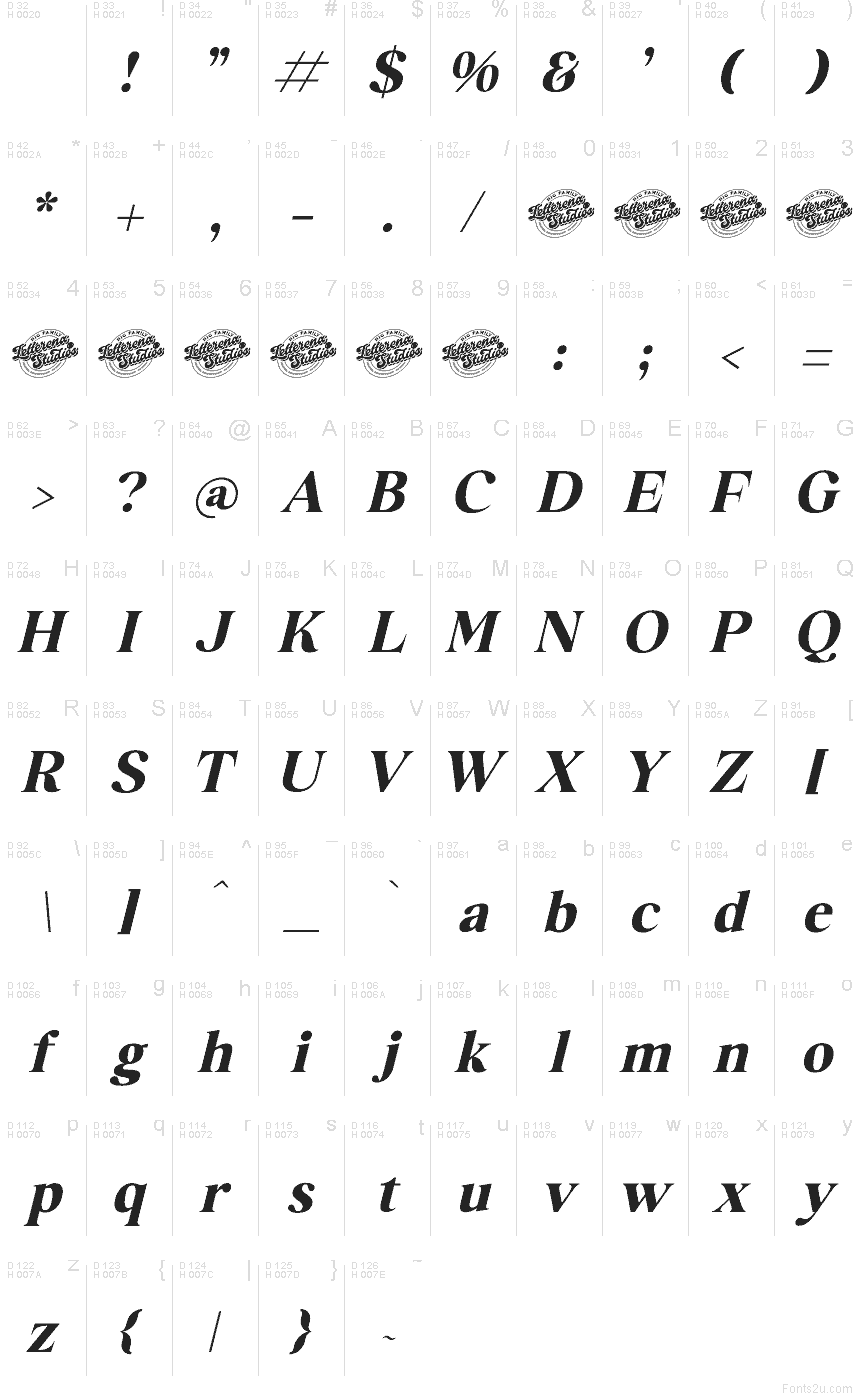
Brilyan Rogale von Letterena Studios ist eine kostenlose serifenbetonte Kursivschrift mit einer modischen, kontrastreichen Ausstrahlung. Die Buchstaben zeichnen sich durch einen eleganten, kalligrafischen Schwung aus und verbinden scharfe Serifen mit weichen Kurven – raffiniert und doch ausdrucksstark.
Sie eignet sich hervorragend für Branding-Projekte, Boutique-Verpackungen, Magazin-Cover, Hochzeitspapeterie sowie Logos aus dem Beauty- oder Schmuckbereich, bei denen eine kostenlose Schrift Eleganz ausstrahlen soll, ohne steif zu wirken. Der fließende kursive Rhythmus ist ideal für kurze Überschriften, Titelkarten und Monogramme, da die Buchstaben visuell ineinandergreifen und eine anmutige, durchgehende Silhouette bilden.